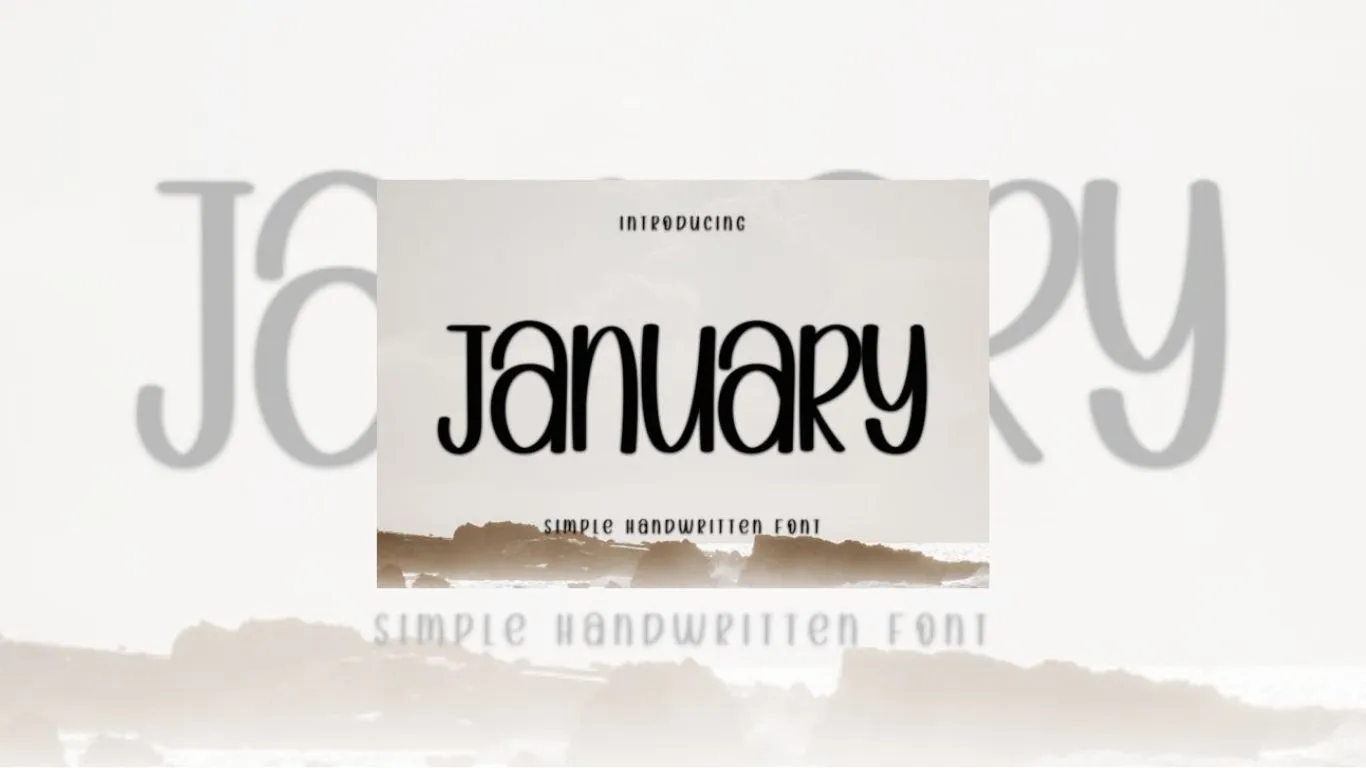
Creative Fabrica 免費字體:January
今天的免費字體是 January,由設計師 PiPi Creative 創作。January 是一款精緻優美的手寫字體,帶有典雅的筆觸。字體目前已累積超過 3,200 次收藏,在 Creative Fabrica 上獲得 5.0 滿分評價,深受設計師好評,同時相容 Cricut 和 Silhouette 切割機,也可輕鬆轉換為網頁字體格式 。